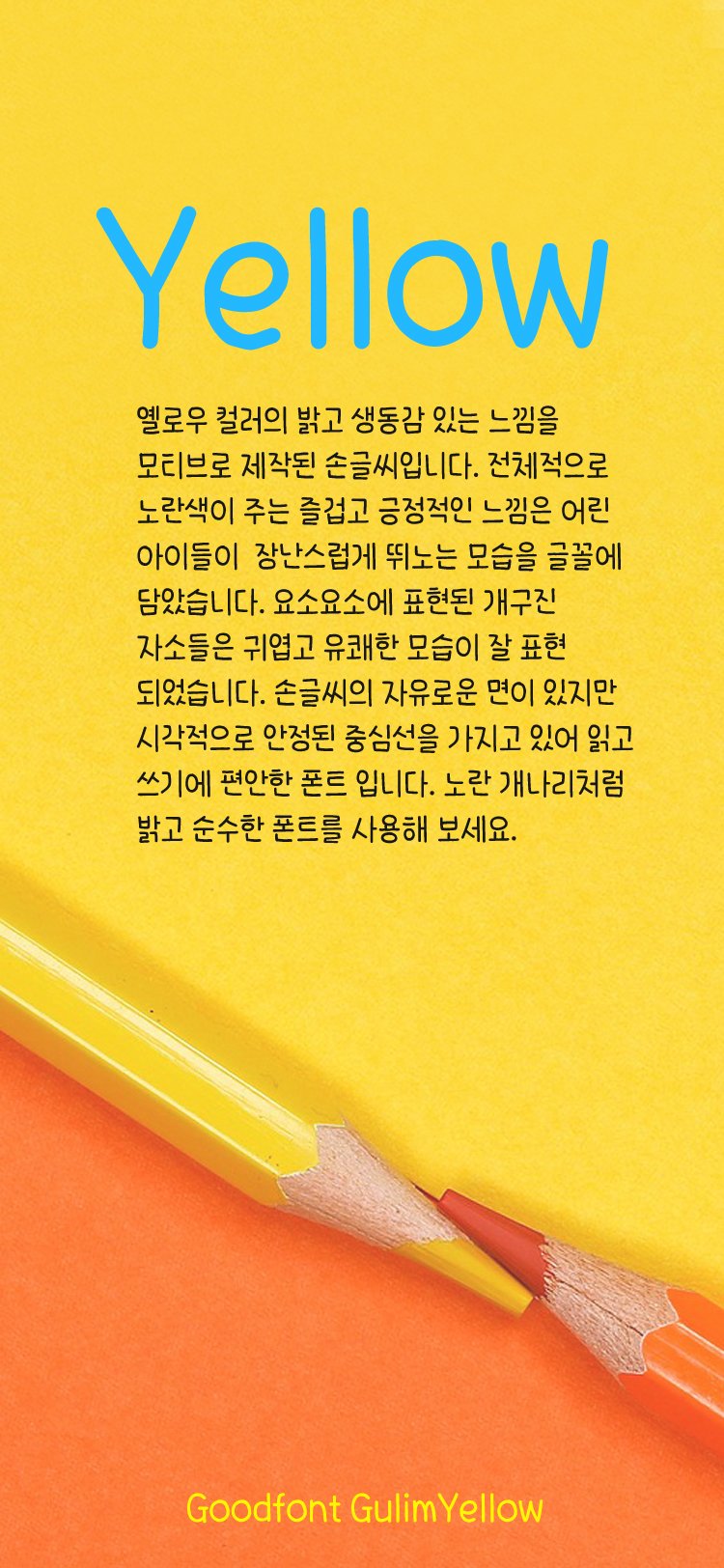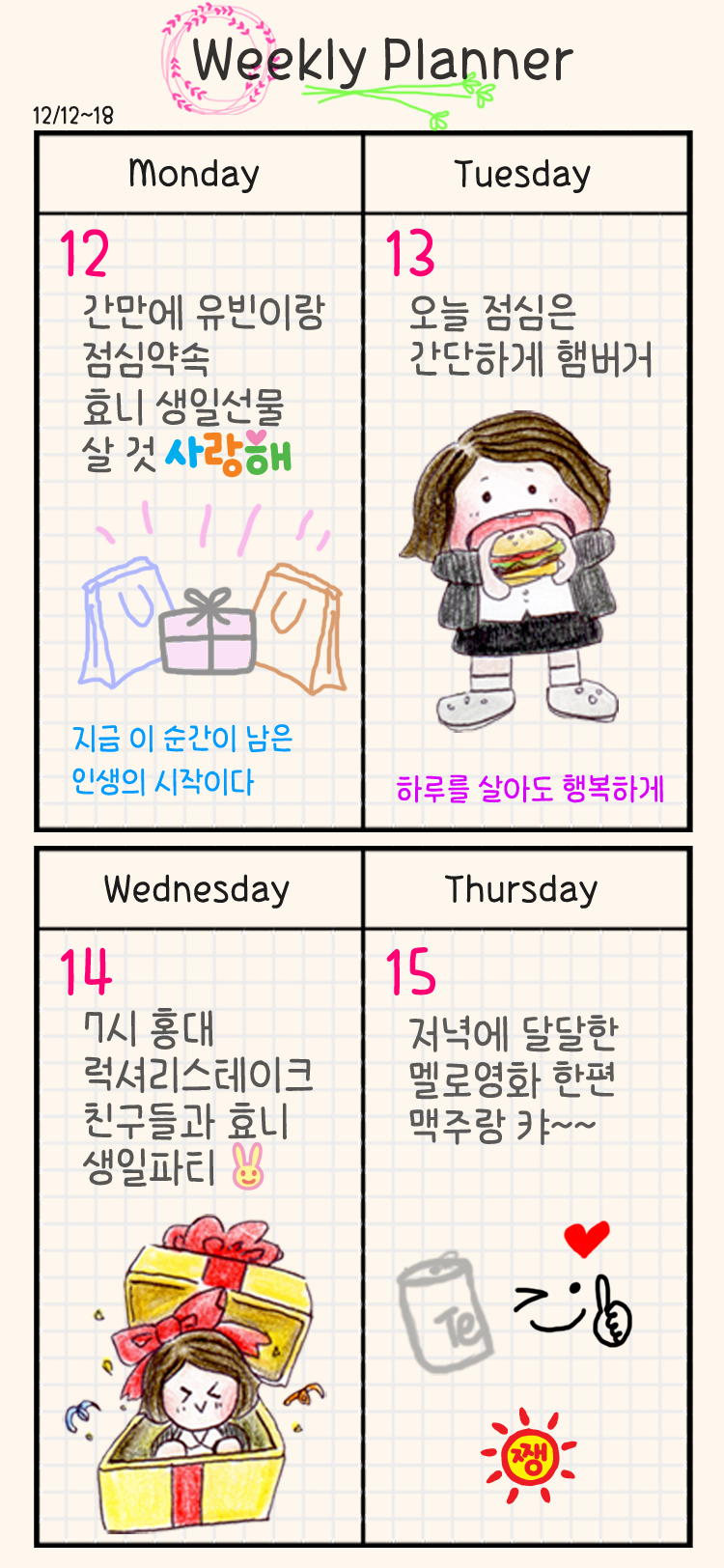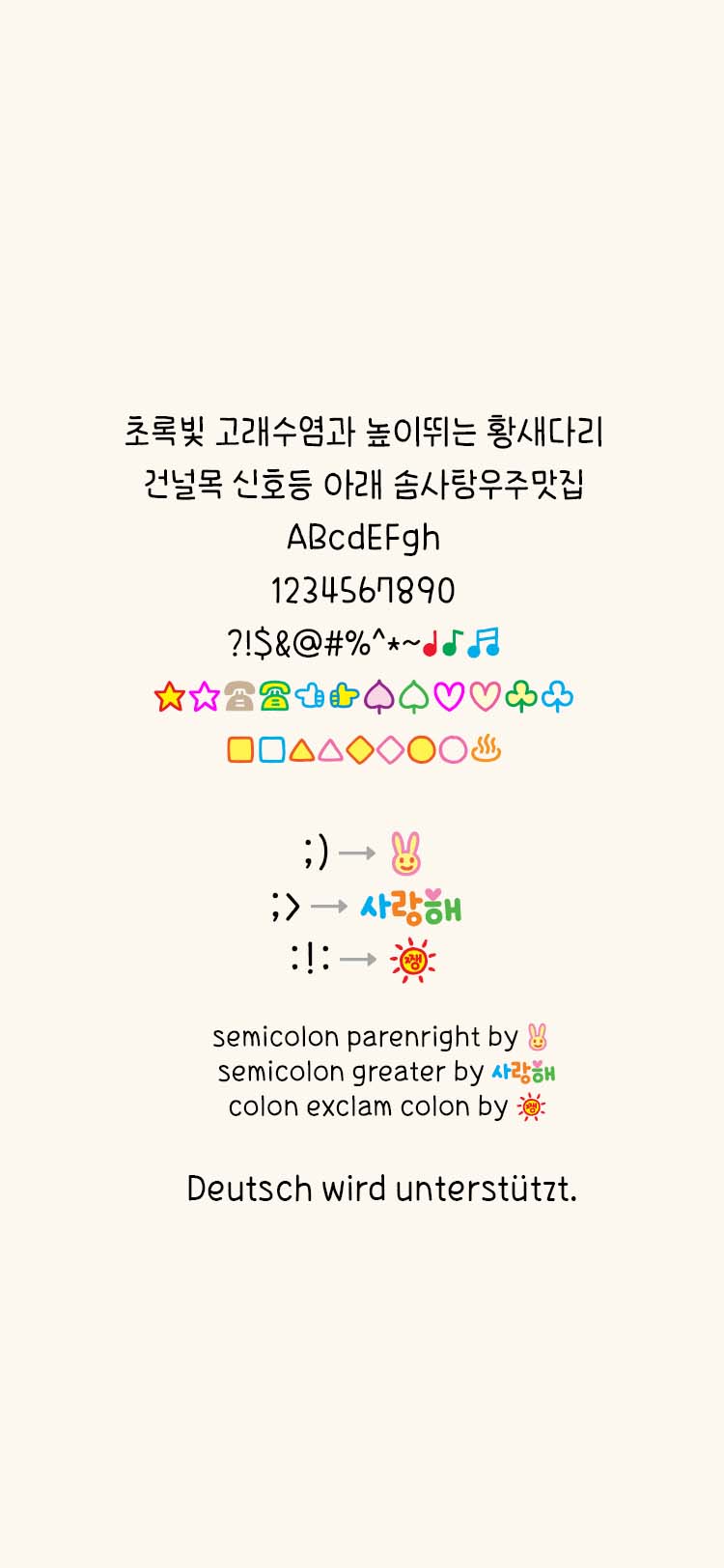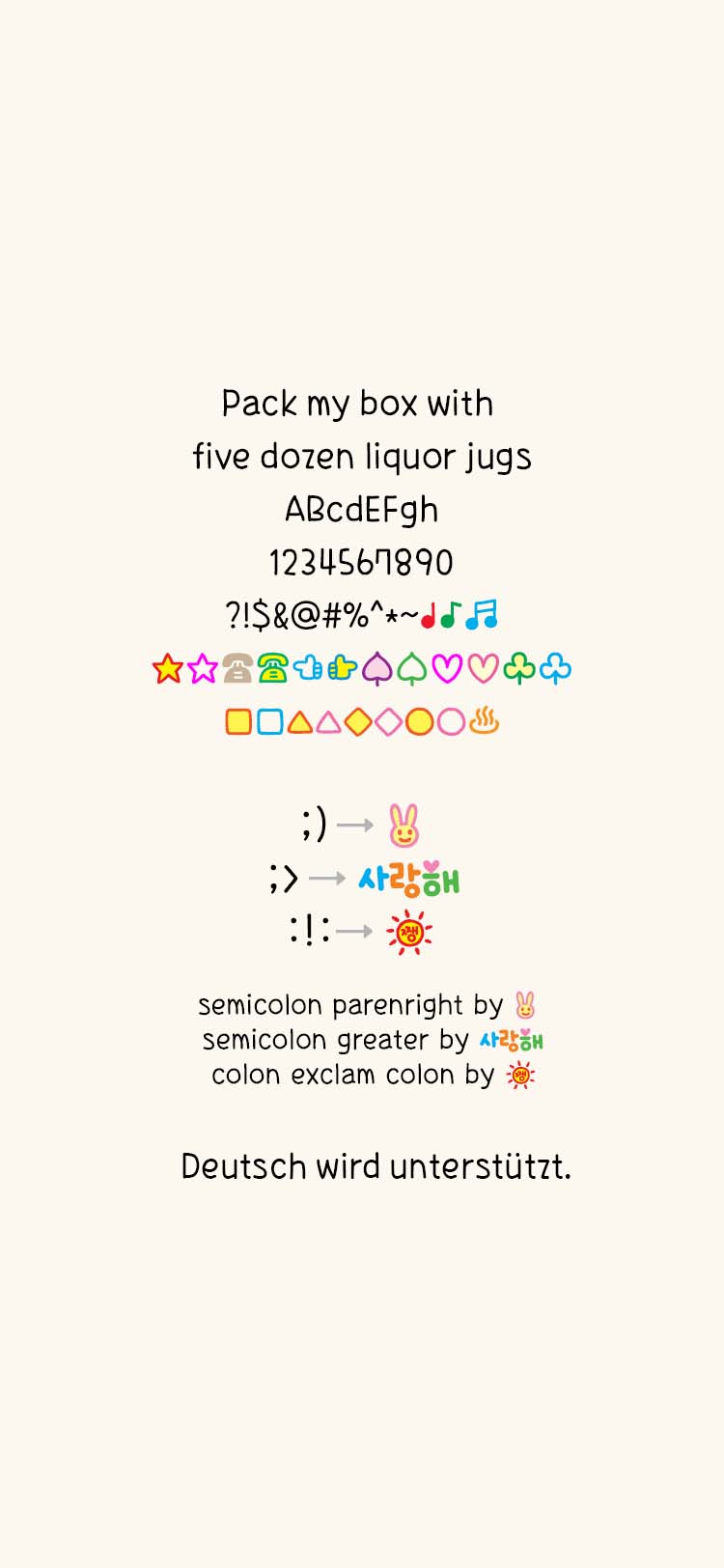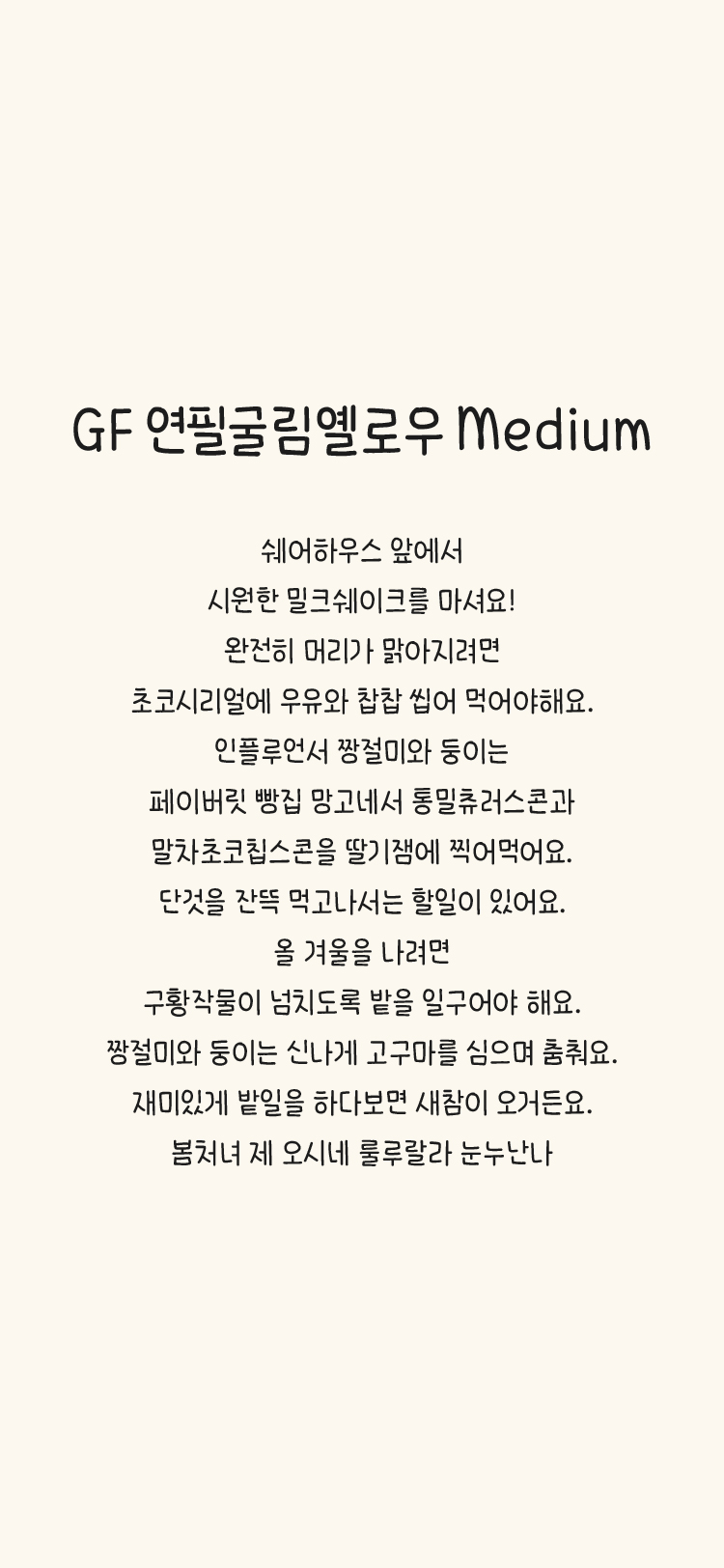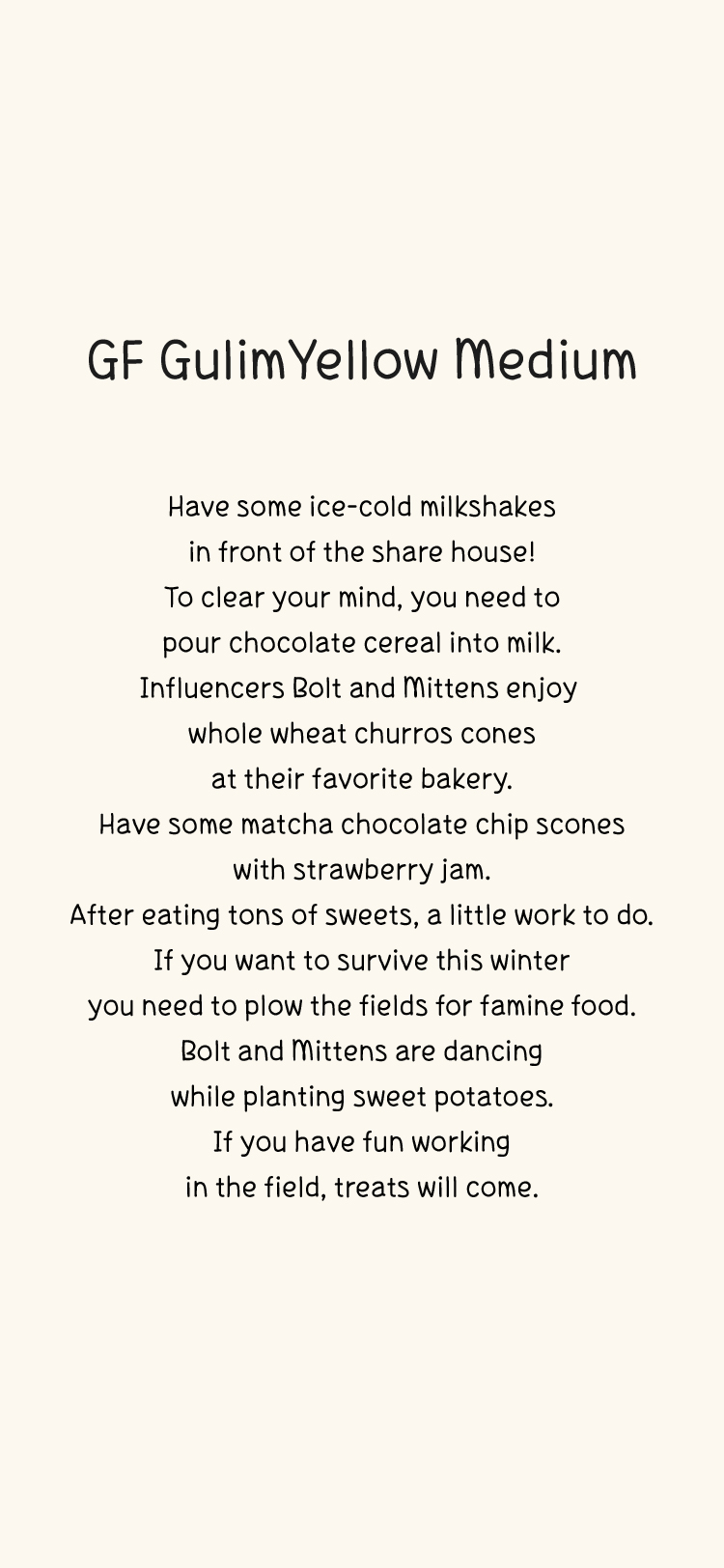
GF 연필굴림옐로우 M Medium
옐로우 컬러의 밝고 생동감 있는 느낌을 모티브로 제작된 손글씨입니다. 전체적으로 노란색이 주는 즐겁고 긍정적인 느낌은 어린 아이들이 장난스럽게 뛰노는 모습을 글꼴에 담았습니다. 요소요소에 표현된 개구진 자소들은 귀엽고 유쾌한 모습이 잘 표현 되었습니다. 손글씨의 자유로운 면이 있지만 시각적으로 안정된 중심선을 가지고 있어 읽고 쓰기에 편안한 폰트 입니다. 노란 개나리처럼 밝고 순수한 폰트를 사용해 보세요.
semicolon parenright by 토끼
semicolon greater by 사랑해
colon exclam colon by 해